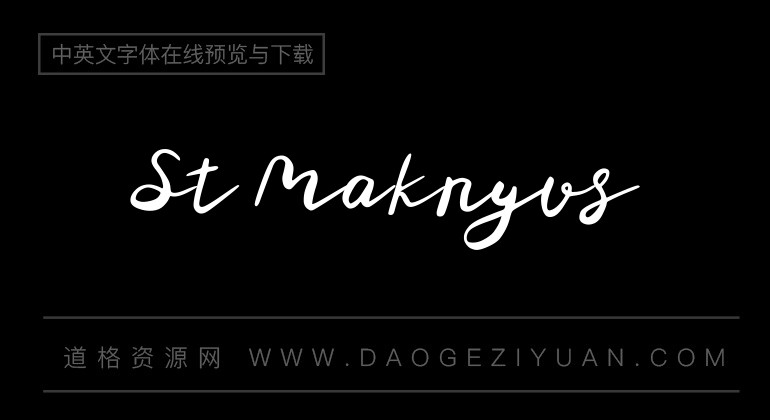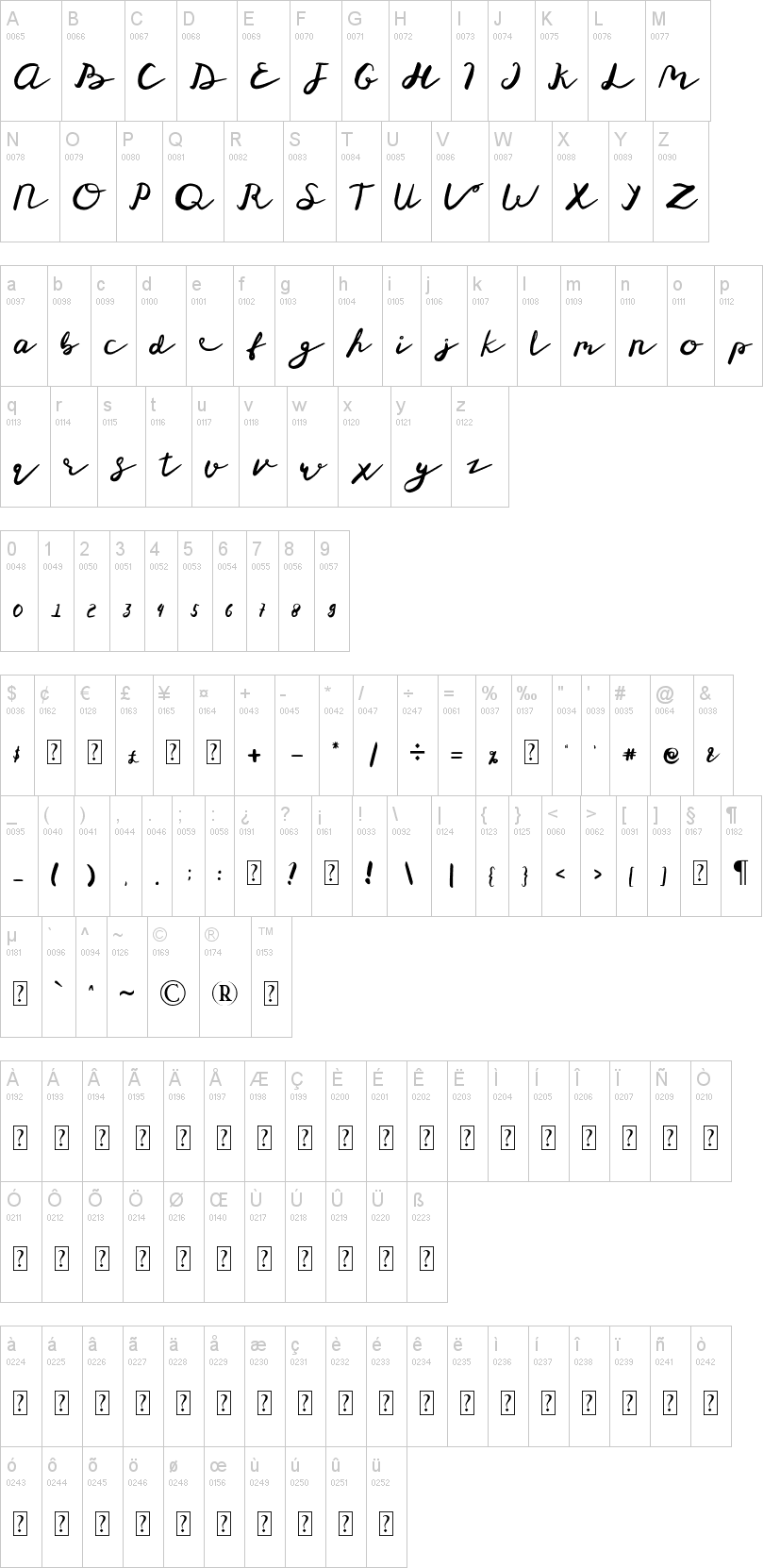
St Maknyus
? St Maknyus 字体是一款具有特殊魅力的手写体字体,它具有温暖、柔和的气息,拥有流畅而优雅的笔画。它的字体设计采用有机的形状,每一个字母都有其独特的表现形式,拥有强烈的视觉冲击力,可以更好地强调文字的视觉效果。它适用于拥有流行风格的设计,也可以为现代设计提供更多的灵活性。
St Maknyus是一款非常不错的手写艺术字体,具有很好的视觉感,适合于文化类的宣传设计、商业类品牌的广告和产品包装设计以及个性化文字排版等较多场景。